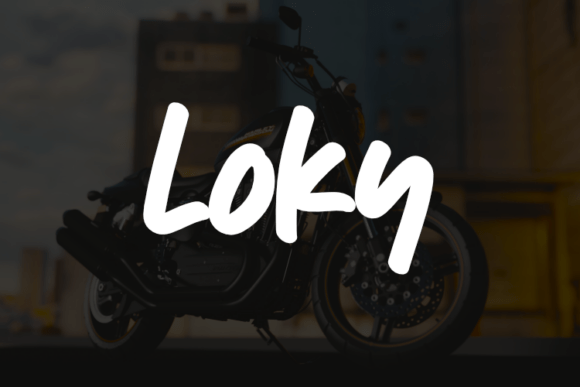
Loky
Lokyのような高品質の素材をお探しの場合、このプレミアムパッケージはクリエイティブなプロジェクトに素晴らしい選択です。
精密に作られたLokyは、クリーンなベクター、滑らかなタイポグラフィ、そして安心のための商用ライセンスを提供します。
POD(オンデマンド印刷)製品、結婚式の招待状、またはソーシャルメディアのグラフィックを作成している場合でも、Lokyは理想的です。